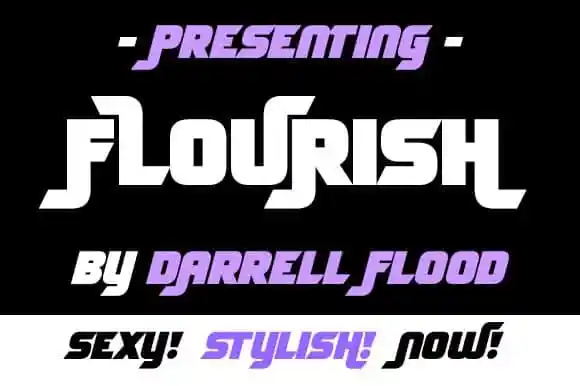
Flourish Display Font – Download Grátis
Flair Display Font é uma fonte condensada desenvolvida por Dadiomouse com um visual moderno. Esta fonte oferece uma ampla gama de alternativas para títulos, permitindo-lhe criar designs sem fronteiras ou bordas. Seu uso simplificado e intuitivo o tornará encantador quando combinado com sua diversidade de designs cênicos. Ideal tanto para criações artesanais quanto gráficas complexas, Flair Display Font é uma escolha perfeita para quem busca um toque especial em seus projetos visuais.